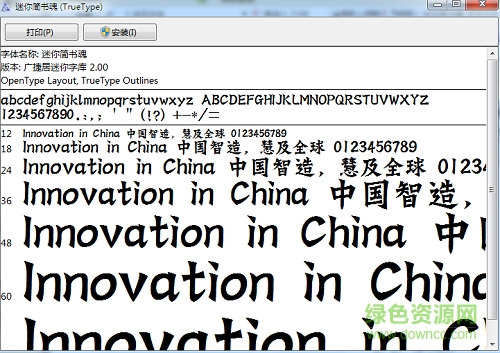
迷你簡(jiǎn)書(shū)魏字體是一款應(yīng)用于廣告創(chuàng)意設(shè)計(jì)方面的簡(jiǎn)體中文字體,該字體以魏碑字為原形而設(shè)計(jì),喜歡的朋友可以來(lái)綠色資源網(wǎng)免費(fèi)下載使用!
迷你簡(jiǎn)書(shū)魏是迷你字庫(kù)打造的一款魏碑字體,字體給人的感覺(jué)有點(diǎn)古典懷舊風(fēng),非常的典雅,大方得體,整體效果更加出色,并且字庫(kù)完整,可以適用于名片設(shè)計(jì)、平面設(shè)計(jì)、廣告設(shè)計(jì)、報(bào)紙雜志、企業(yè)LOGO、商標(biāo)注冊(cè)、電視臺(tái)廣告等領(lǐng)域!